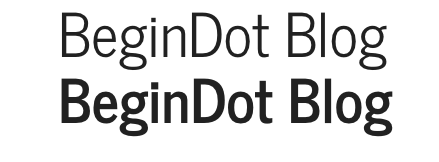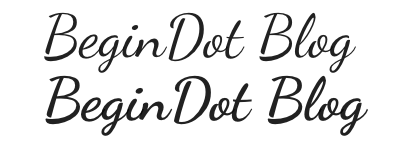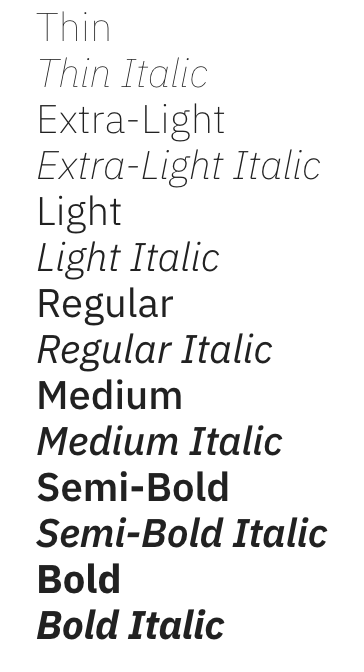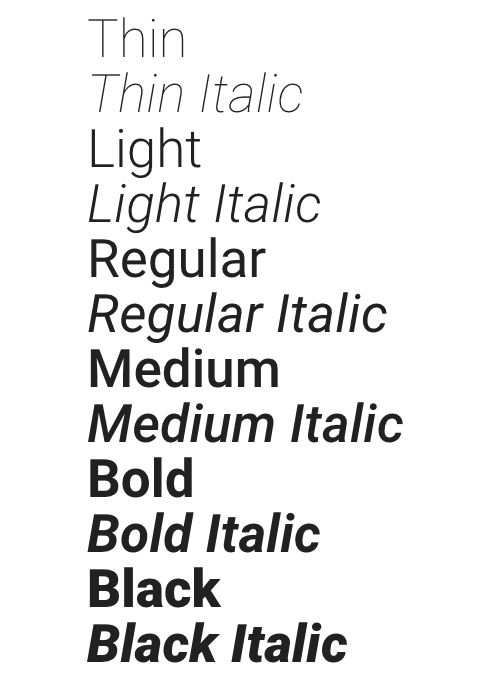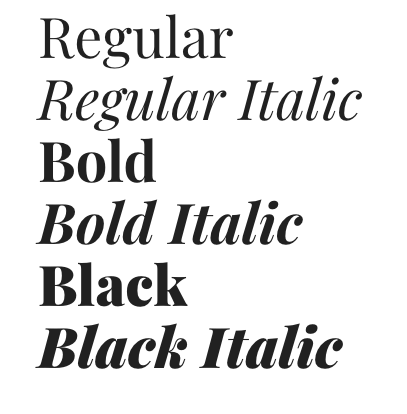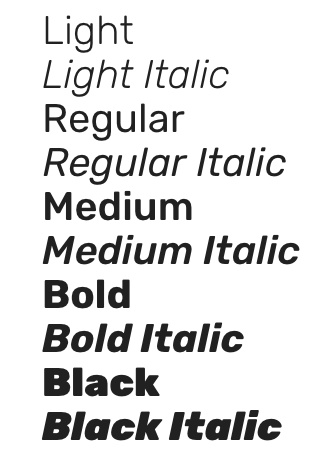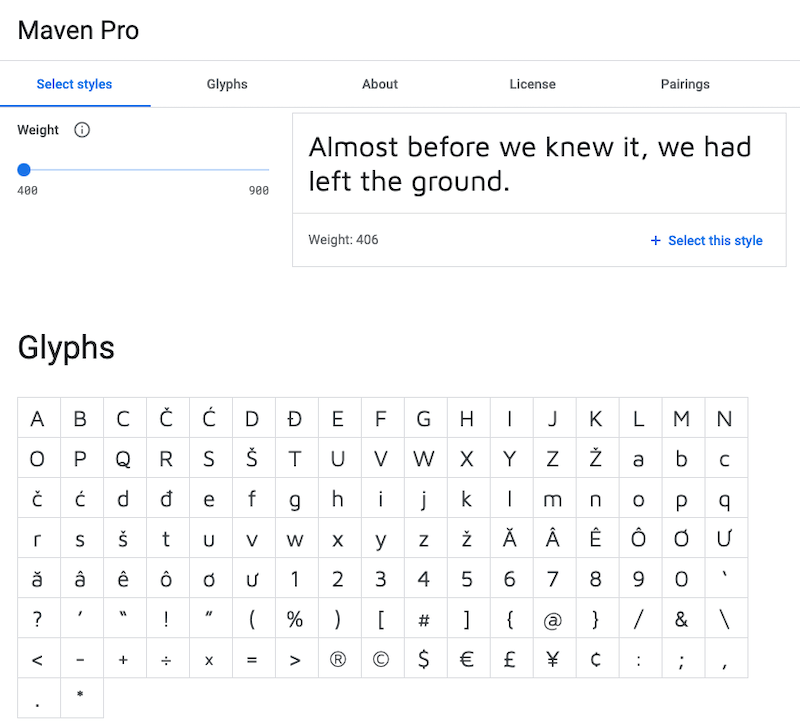
30+ แบบอักษร Google ที่ดีที่สุดสำหรับเว็บไซต์ของคุณ
การสร้างเว็บไซต์เพื่อเผยแพร่ตัวเองไปทั่วโลก การเปิดเผยตัวเองสู่โลกกว้างอาจเป็นเรื่องที่น่าตื่นเต้นและค่อนข้างล้นหลามในเวลาเดียวกัน
ในช่วงเวลาที่เครือข่ายทั่วโลกเต็มไปด้วยเนื้อหาและบริการที่คล้ายคลึงกัน การทำให้เครือข่ายของคุณโดดเด่นและสะดุดตาเป็นสิ่งที่จำเป็น
สำหรับสิ่งนี้ สิ่งสำคัญคือต้องเข้าใจว่าการโฆษณาวรรณกรรมมีความสำคัญเพียงใด ดังนั้นเราจึงนำเสนอ แบบอักษร Google ที่หลากหลายสำหรับเว็บไซต์ที่จะทำให้พาดหัวข่าวของคุณโดดเด่นและดึงดูดการเข้าชมเนื้อหาของคุณ
หลังจากเปิดตัวในปี 2010 ฟอนต์ของ Google ก็ได้รับเสียงชื่นชมอย่างต่อเนื่อง เนื่องจากฟอนต์เหล่านี้ถูกใช้อย่างกว้างขวางทั้งในด้านอาชีพและส่วนบุคคล เมื่อคุณนำเสนอแนวคิดและเนื้อหาของคุณ ความสามารถในการอ่านนั้นมีความสำคัญสูงสุด
แบบอักษรที่ซับซ้อนอาจดูดีบนกระดาษ แต่อาจไม่สามารถสื่อสารข้อความของคุณได้เนื่องจากไม่สามารถเข้าใจได้ง่ายในทันที
คุณต้องการบางสิ่งบางอย่างที่จะติดอยู่ในใจของผู้ชมเพียงแค่มองแวบเดียว ที่นี่ เราได้รวบรวม รายการแบบอักษร Google ที่ครอบคลุมซึ่งจะช่วยให้บล็อกหรือเว็บไซต์ของคุณดึงดูดสายตามากขึ้น
นอกจากนี้ ถึงเวลาแล้วที่เราจะทำลายความซ้ำซากจำเจของ Times New Roman และกระตุ้นความกระตือรือร้นในขณะเดียวกันก็รักษาความน่าเชื่อถือของเราไว้ด้วย!
เปิด Sans
Open Sans เป็นหนึ่งใน Google Fonts ที่ได้รับความนิยมและใช้กันอย่างแพร่หลาย เป็นแบบอักษร sans serif ที่ออกแบบโดย Steve Matteson
การออกแบบฟอนต์ Open Sans ที่เรียบง่ายและสะอาดตาทำให้ฟอนต์นี้เป็นที่นิยมในหมู่บล็อกเกอร์และนักเขียน แม้แต่ Google ยังใช้แบบอักษร Open Sans สำหรับจำนวนหน้า
- เหมาะสำหรับงานพิมพ์
- เหมาะสำหรับอุปกรณ์พกพา
- เป็นที่นิยมในหมู่บล็อกเกอร์
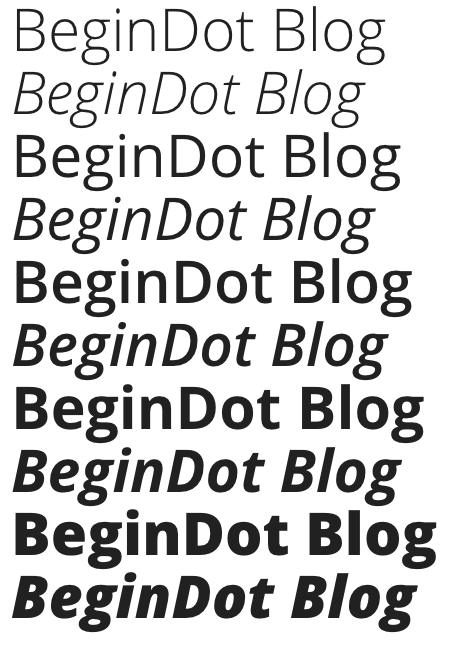
ลาโต้
Lato เป็นแบบอักษรโอเพ่นซอร์สที่ใช้กันทั่วไปอีกแบบหนึ่ง ฟอนต์ Serif นี้เดิมออกแบบเป็นแบบอักษรองค์กร ออกแบบในปี 2010
- เปิดสำหรับสาธารณะ
- มีให้เลือกหลายรุ่น
- ตัวเลือกที่ดีสำหรับบล็อก
อักษร โวลกรณ์
แบบอักษรนี้มีความละเอียดอ่อน มันค่อนข้างเจียมเนื้อเจียมตัวและได้สัดส่วนมาก ทำให้สบายตา มันเข้ากันได้กับหกทั้งหมดและเมื่อมันเป็นตัว หนา หรือ ตัวเอียง
สิ่งนี้สำคัญเพราะช่วยให้คุณสามารถกลั่นกรองพาดหัวข่าวได้ตามที่คุณต้องการ โดยไม่ต้องกังวลว่ามันจะออกมาเป็นอย่างไร
- มี 8 แบบ
- สามารถใช้กับตัวอักษรขนาดเล็กได้เช่นกัน
- ตัวอักษรเนื้อและสีเข้ม
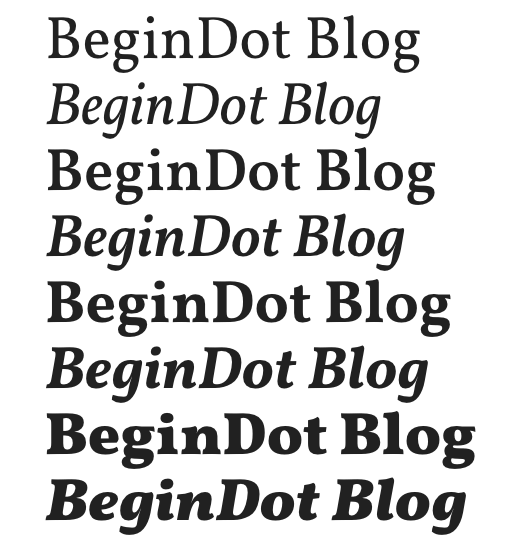
บรีเซอริฟ ฟอนต์
บรีเซอริฟมีความนุ่มนวลรอบขอบ ทำให้ดูหรูหราแต่ดูมีเสน่ห์ เป็นฟอนต์ที่ค่อนข้างเหมาะสมหากคุณต้องการเน้นคีย์เวิร์ดบางคำหรือดึงดูดความสนใจไปที่วลีหรือประโยคเฉพาะ
เป็นที่นิยมกันอย่างแพร่หลายสำหรับหัวข้อข่าวหรือหัวข้อย่อยเนื่องจากทำให้ประโยคโดดเด่น
- ตั้งตรงอย่างเคร่งครัด
- ได้รับความนิยมสูงสุดในสหรัฐอเมริกา
- ได้รับการตั้งค่าทันทีหลังจากเปิดตัวในปี 2551
ดรอยด์ ฟอนต์
สมาคม Droid ประกอบด้วย Droid Sans, Droid Serif และ Sans Mono และเข้ากันได้กับเนื้อหาทุกประเภทในแง่ของย่อหน้า หัวเรื่อง หัวเรื่องย่อย หรือบทกลอน
สิ่งเหล่านี้บางและคม แต่เมื่อทำให้หนาขึ้นแล้ว พวกมันเติมเต็มช่องว่างอย่างสวยงามเพื่อดึงดูดความสนใจของคุณ สามารถใช้แทน Georgia หรือ Verdana ของ Microsoft Word ได้
- กระจายไปทั่วสามประเภท
- อเนกประสงค์ที่มีหลายตัวเลือก
- ที่สะดุดตา
บาร์โลว์ฟอนต์
Barlow เป็นอีกหนึ่งแบบอักษรฟรีของ Google คุณภาพสูงที่คุณสามารถใช้บนเว็บไซต์ของคุณได้ เช่นเดียวกับโครงการอื่นๆ ฟอนต์นี้ดูคมชัดดีสำหรับผู้อ่าน เราใช้ฟอนต์นี้บนไซต์น้องสาวของเราและมันก็ดูดี
เราใช้แบบอักษรนี้สำหรับชื่อเรื่องและหัวเรื่อง ฟอนต์นี้มีหลายเวอร์ชั่น ทั้งแบบหนา แบบกึ่งหนา และแบบย่อ คุณจึงมีความหลากหลายที่จำเป็นสำหรับโครงการของคุณ
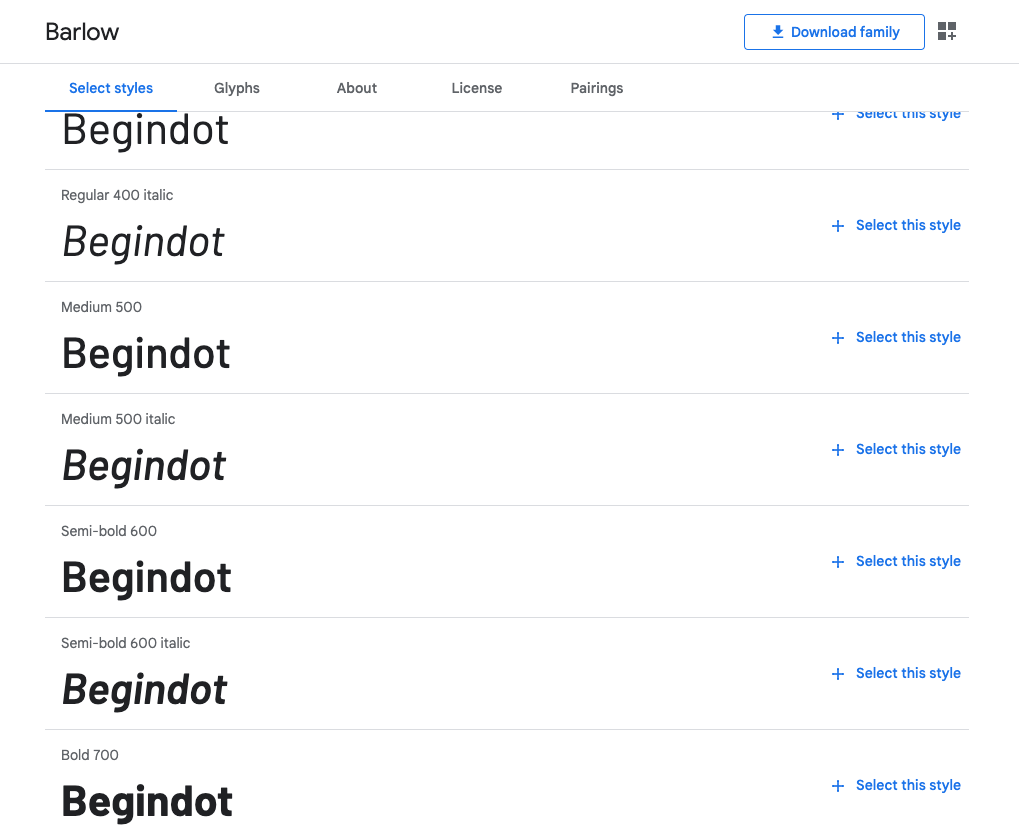
แบบอักษร ห้องโดยสาร
แบบอักษรนี้สามารถผสมผสานกับการตั้งค่าหรือพื้นหลังใด ๆ และจะให้ความรู้สึกชัดเจนและอ่านง่ายเช่นเดียวกัน
การเพิ่มหรือลดขนาดจะไม่ทำให้อ่านง่าย ดังนั้นคุณจึงมีอิสระในการสร้างสรรค์มากขึ้นในการสำรวจความคิดของคุณและนำเสนออย่างมีประสิทธิภาพ
ห้องโดยสารยังเฉียบคมและแม่นยำ ทำให้ดูเป็นทางการหากเว็บไซต์หรือบล็อกของคุณสนใจธุรกิจหรือผู้ชมที่เป็นองค์กร หรือผู้ที่มีความอดทนต่อการเขียนเพ้อฝันน้อยมาก
- การกระจายน้ำหนักเสียงเดียว
- ตัวอักษรคมชัดและแม่นยำ
- เส้นโค้งที่ปรับด้วยแสง
ล็อบสเตอร์ ฟอนต์
ฟอนต์จะแสดงตัวเอียงตามค่าเริ่มต้น นอกจากนี้ยังเป็นตัวหนาโดยธรรมชาติ และการทำให้ตัวหนามากขึ้นนอกเหนือจากตัวเอียงจะดึงดูดความสนใจหรือความสนใจได้อย่างแน่นอน
มันคล้ายกันมากกับตัวอักษรเล่นหางที่ตัวอักษรติดกันแทบจะไม่มีช่องว่าง
- ตัวหนาและตัวเอียงตามค่าเริ่มต้น
- ส่วนติดต่อเล่นหางหนา
- เหมาะสำหรับหัวเรื่อง
หนังสือเกาดี้ 2454
สำหรับผู้ที่ชื่นชอบข้อความคลาสสิกหรือต้องการให้ความรู้สึกแบบข้อความเก่าสำหรับเว็บไซต์ของคุณ Goudy เหมาะอย่างยิ่ง
มุมมองของมันไม่ได้ประนีประนอมกับความสามารถในการอ่านและการใช้ถ้อยคำที่หนักแน่นทว่าแข็งทื่อของเนื้อหาของคุณทำให้บล็อกของคุณดูโบราณ
เหมาะสำหรับธีม ประโยค และเนื้อความ
- ตัวเลือกคลาสสิกที่คุณไม่ผิดพลาด
- แกะสลักอย่างสวยงามแต่ดูเป็นมืออาชีพ
- ใช้เป็นประจำในแคนาดาและสหรัฐอเมริกา
แม้ว่าคำอุทธรณ์จะมีความสำคัญ แต่ความสามารถในการอ่านและความชัดเจนนั้นมีความสำคัญกว่า เพราะสิ่งเหล่านี้เป็นตัวตัดสินว่าคุณถ่ายทอดแนวคิด ความเห็น หรือข้อความของคุณไปยังผู้อ่านได้สำเร็จหรือไม่
ดังนั้น แม้ว่าคุณต้องการให้เว็บไซต์ของคุณมีการตกแต่งหรือดึงดูดใจ แต่คุณก็อาจไม่ต้องการทดสอบมากเกินไป